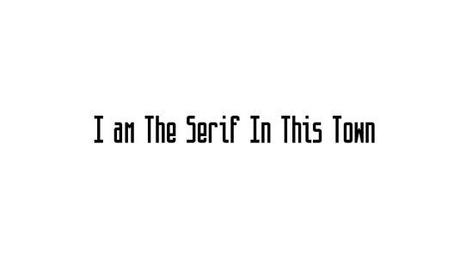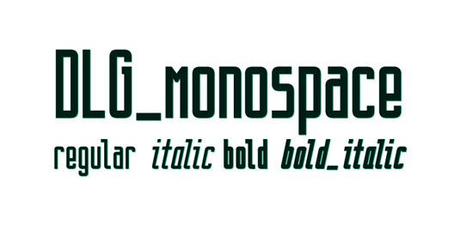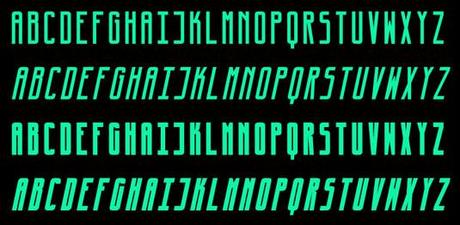
Font Del Giorno: DLG Monospace
DLG Monospace protagonista della nostra rubrica font del giorno. Sappiamo tutti l’importanza del contenuto nel web design e il font è lo strumento per dare ancora più enfasi e forza al contenuto della nostra pagina web e farlo diventare il re incontrastato. “Content is King” ma il carattere giusto lo rende ancora più usabile e fruibile. La scelta del font può compromettere la riuscita della comunicazione del nostro sito web. Il carattere giusto è quello strumento che permette di inserire il nostro messaggio in una grafica accattivante senza far perdere omogeneità, stile e bellezza a tutta la nostra pagina web. Anzi, il font idoneo rafforza il messaggio che vogliamo trasmettere, lo rende più visibile e usabile da parte dell’utente. Detto questo, oggi voglio condividere con te questo bellissimo ed elegantissimo font, DLG Monospace. Purtroppo, come succede per tutte le cose belle, uniche e originali, questo carattere non è gratuito, ma è a pagamento! Ma si sa, per la costruzione di un design accattivante e di una comunicazione efficace, emozionante, chiara, semplice e diretta si deve pur investire qualche euro. Quindi se vuoi un font elegante, in grado di regalare emozioni e in stile con il moderno web design, ecco DLG Monospace.
DLG Monospace Font, un carattere molto elegante, sobrio, pulito e fresco in grado di suscitare emozioni nell’animo dell’utente e di rendere la nostra comunicazione efficace e diretta senza perdere di bellezza e unicità. Questo carattere per me è formidabile perchè ci permette di passare il nostro messaggio in maniera semplice ma con stile, non risulta pesante ed è facile da leggere. Forme sobrie e linee pulite fanno di questo font un must have per ogni web designer o web developer. DLG Monospace è stato ideato dal designer polacco Sebastian Cabaj che ha voluto progettare un font fashion dallo stile minimal che si potesse interfacciare con le linee guida del flat design. Credo che questo carattere sia molto utilizzato ed ideale per la costruzione di branding identity, poster design e visual communication.